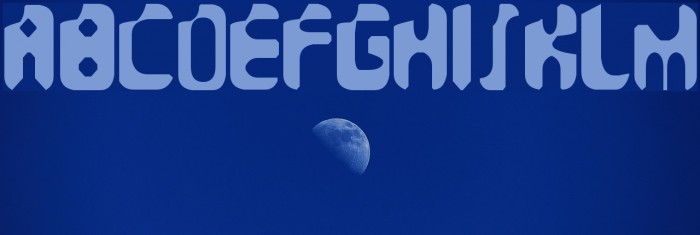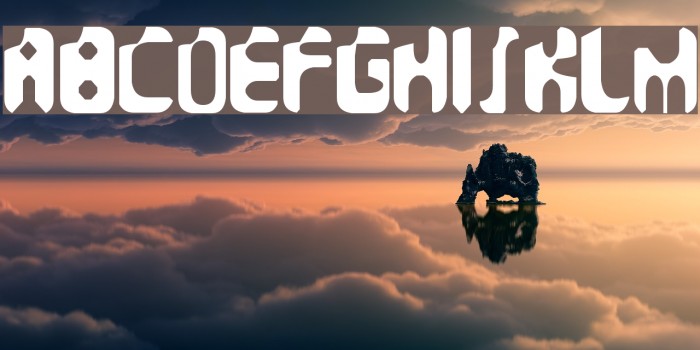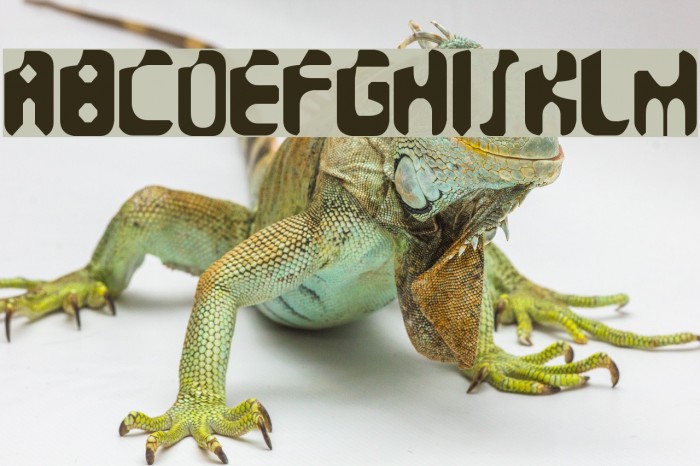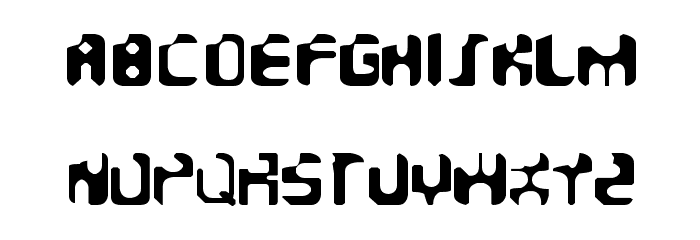
Faeronic Font
| Progetti proposti | Ideal for sci-fi themed projects, video game titles, posters, and branding that requires a modern and edgy look. |